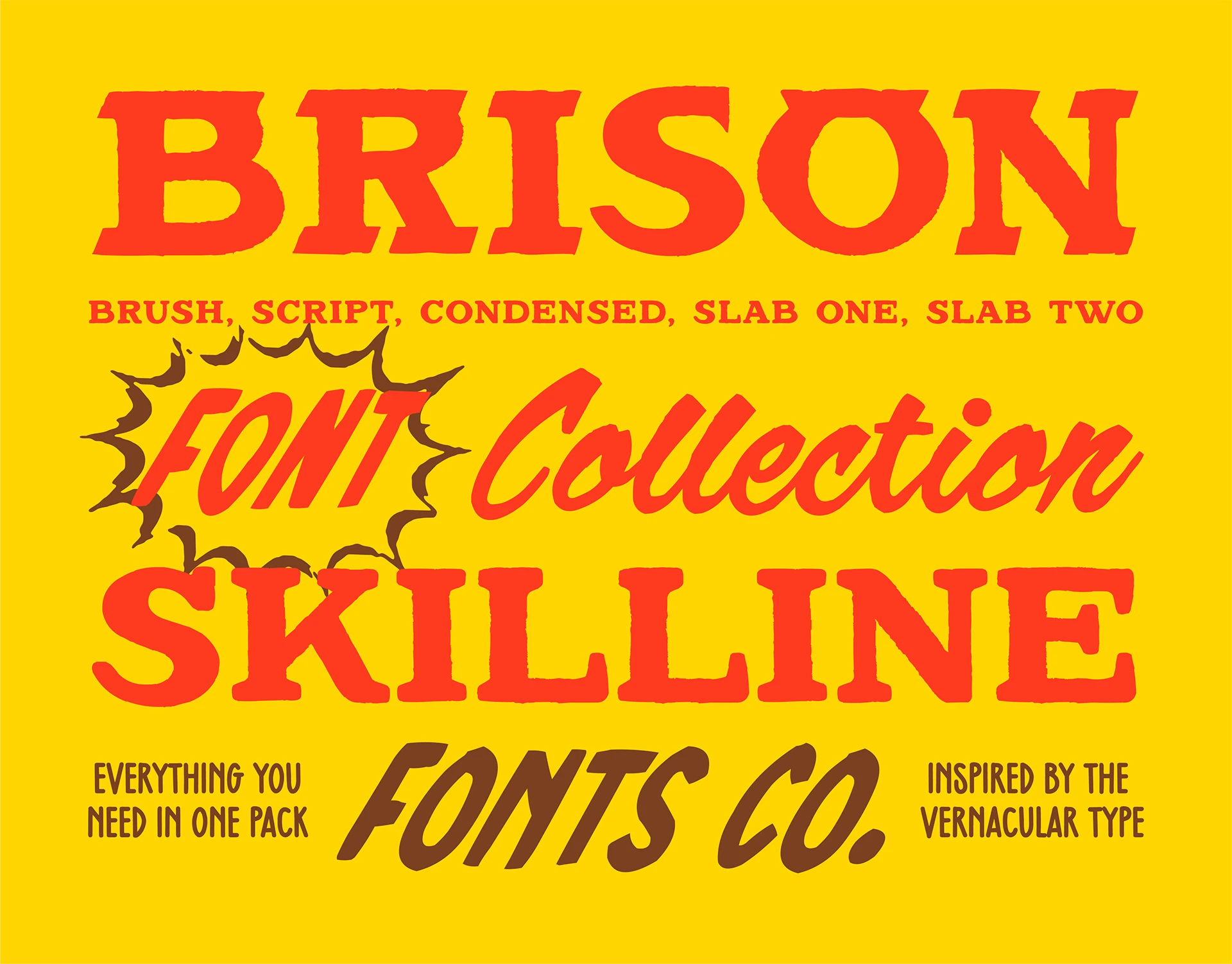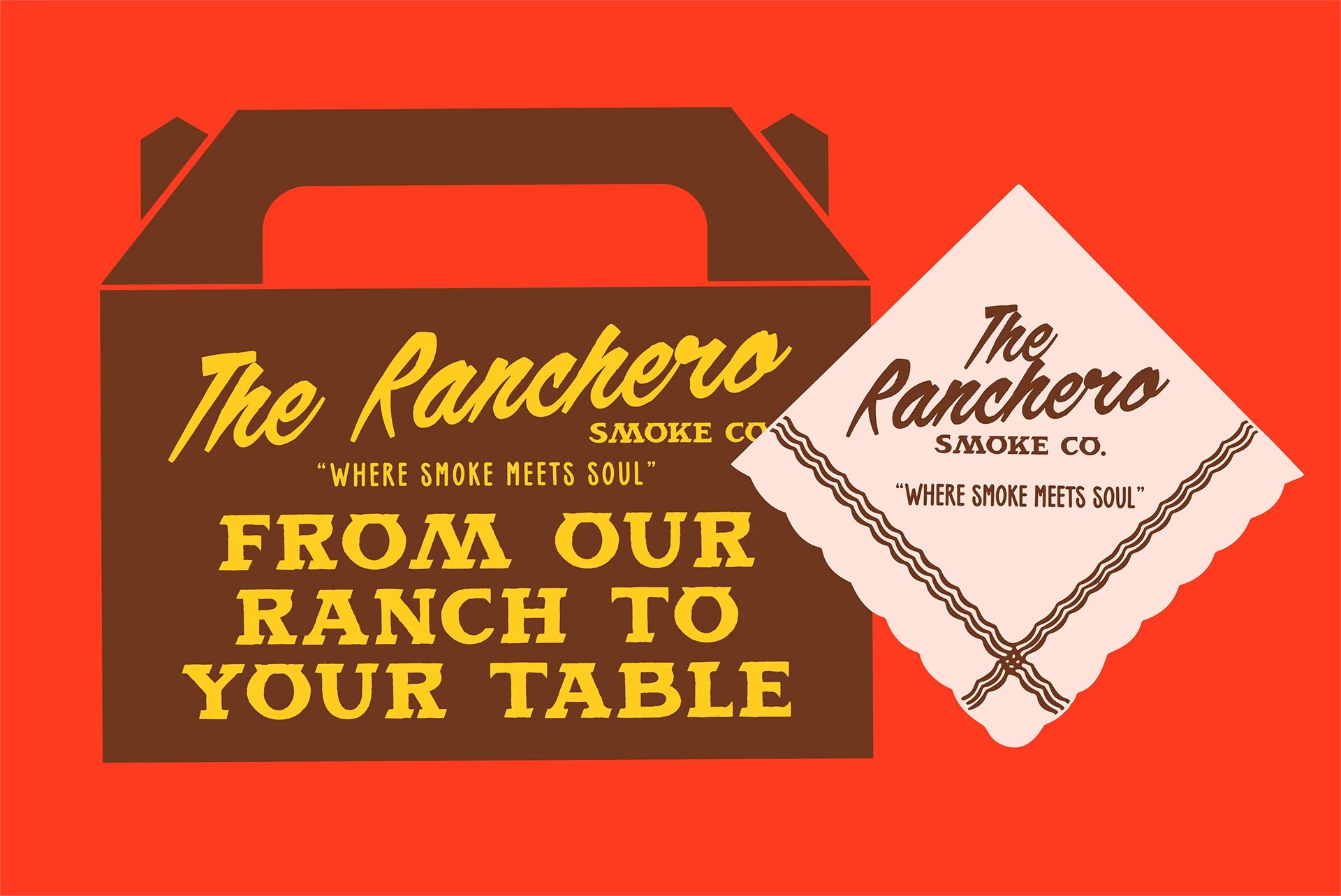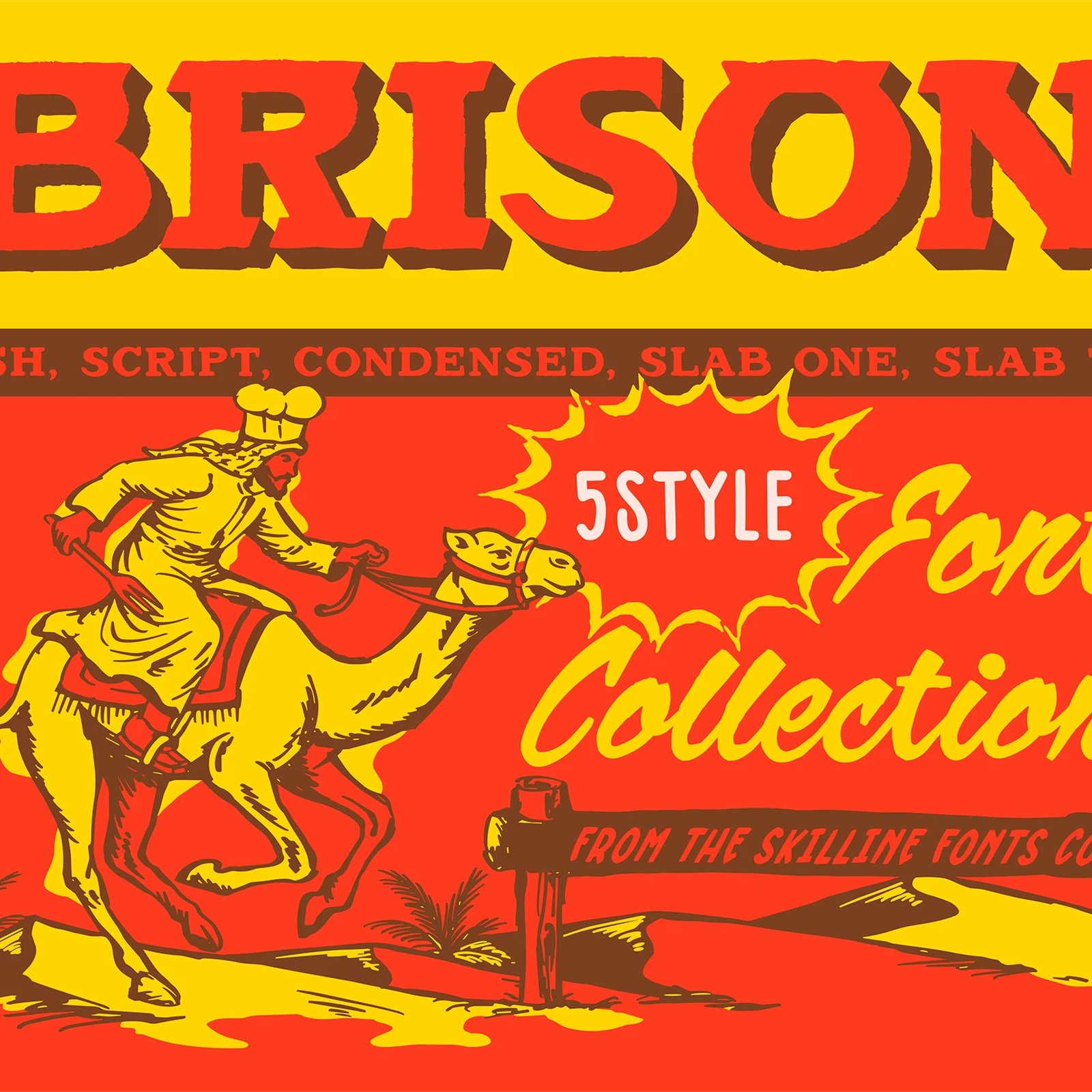
SFC Brison là một bộ font phong cách western retro đầy mạnh mẽ đến từ Skilline Fonts Co. Với 5 kiểu dáng khác nhau, bộ font này cực kỳ phù hợp cho các dự án branding quán đồ nướng BBQ, nhãn nước sốt hay các thiết kế bao bì mang hơi hướng Americana.
Thông thường, các bộ font western retro chỉ có một độ dày duy nhất. Nhưng với Brison, https://www.behance.net/gallery/250985599/SFC-Brison-Font-Collection đã đầu tư kỹ lưỡng hơn khi tạo ra 5 style dạng condensed (cô đọng) nhưng vẫn giữ được sự đồng nhất về x-height và đường ascender cho toàn bộ gia đình font. Các nét chữ có phần serif được làm quá lên để tạo cảm giác về khối lượng khi hiển thị ở kích thước lớn, gợi nhớ đến những biển hiệu nhà khói cũ hay bảng tên ở các trang trại, nơi mà chữ nghĩa phải đọc rõ từ khoảng cách xa. Với tông màu than và nâu đất chủ đạo, bộ font mang lại cảm giác phong trần như đã trải qua nắng gió sa mạc. Từng cặp ký tự đều được kiểm tra trên các bối cảnh thực tế như thực đơn, nhãn dán hay tag quần áo để đảm bảo tính ứng dụng tốt nhất.
SFC Brison: Một cá tính xuyên suốt 5 kiểu dáng
Vấn đề thiết kế khó nhất ở đây là làm sao để đa dạng mà không bị loãng. Một bộ font giữ được chất Western ở bản Regular thì cũng phải giữ được phong thái đó ở bản Bold. Brison đã giải quyết cực tốt bằng cách giữ nguyên tỷ lệ condensed và chỉ tập trung tăng độ dày cho phần serif. Những style nặng hơn mang lại cảm giác vững chãi như chữ khắc gỗ, trong khi những style nhẹ hơn lại giống kiểu in ấn trên các bao bì Americana cổ điển. Chính sự linh hoạt này giúp Brison có giá trị thương mại cao, khi có thể vừa làm tiêu đề bảng hiệu, vừa làm nhãn chai cho cùng một dự án.
Skilline Fonts Co. tạo ra Brison nhắm đến các designer làm việc trong mảng thực phẩm, đồ uống và thời trang – những lĩnh vực mà phong cách Americana luôn được ưa chuộng. Với hệ thống 5 style đi kèm, bộ font này giúp các nhà thiết kế dễ dàng thay đổi trọng lượng chữ mà không cần đổi sang font khác, giữ cho hệ thống nhận diện thương hiệu luôn đồng bộ và chuyên nghiệp.